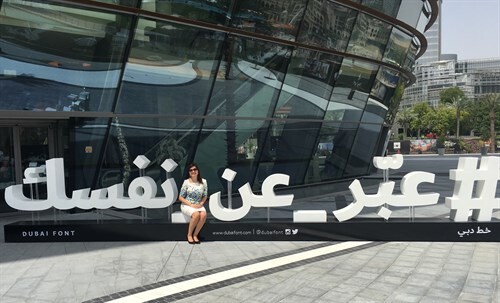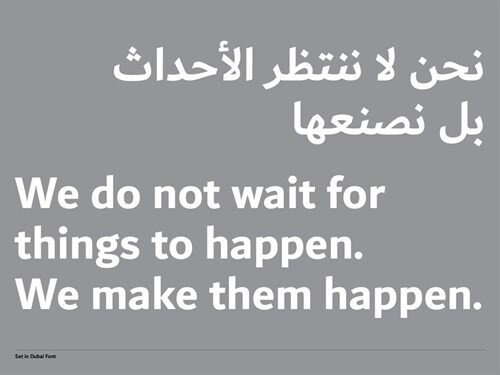
Dubai Font : une police de caractères d’avenir pour une ville et ses habitants
Le Conseil exécutif de Dubaï s’est associé à Microsoft et Monotype pour créer une famille de polices qui reflète la nature énergique et dynamique de Dubaï. Plus qu’une police de caractères gouvernementale, cette famille typographique - qui a été librement diffusée pour un usage public et est disponible dans Microsoft Office 365 - a été conçue pour être une voix harmonieuse à la fois dans les écritures latine et arabe.
Si plusieurs villes ont investi dans leurs propres polices de caractères sur mesure, ce qui distingue Dubai Font est son partenariat avec Microsoft et sa distribution gratuite pour l’usage public et gouvernemental. Alors que de nombreuses typographies urbaines ont pour cœur le tourisme ou une fonction utilitaire, Dubai Font va au-delà. Elle devient également une voix typographique pour la population qu’elle représente.
Pour Nadine Chahine, alors directrice typographe chez Monotype, le projet s’est également inscrit dans une perspective personnelle. Elle a vécu et enseigné à Dubaï, s’y rend régulièrement depuis 2005 et a été témoin de la croissance et du développement de la ville. La création d’une famille de polices sur mesure a été l’occasion d’exprimer une partie de la personnalité et de l’héritage de la ville, ainsi que de designer ses deux composantes - les caractères latins et arabes - main dans la main. Le plus souvent, les deux alphabets sont développés séparément, ce qui a donné à Dubai Font l’honneur d’être la première police de caractères intégrée dans Microsoft Office dont les alphabets latin et arabe ont été créés en même temps.
L’harmonie entre le latin et l’arabe était essentielle au design, et reflétait l’harmonie avec laquelle tant de nationalités différentes à Dubaï en sont venues à vivre ensemble.
Pour gérer ce processus, il a fallu des vérifications régulières avec les designers de l’équipe, échangeant des fichiers afin de s’assurer que les différents scénarios fonctionnaient ensemble. Donc travailler en harmonie pour développer le design global. De subtiles modifications du design ont été exigées afin de créer une compatibilité entre les deux écritures sans sacrifier l’authenticité de l’une ou l’autre. Par chance, certaines caractéristiques de l’arabe peuvent être joliment assorties à certains styles du design latin.
« En arabe, nous avons beaucoup de courbes peu profondes avec des changements de direction soudains. Ce type de caractéristiques était essentiel au design », explique Chahine. « Nous devions également garder une référence au mouvement du stylo, mais subtile, car c’est une police sans serif, donc peu calligraphique. »
La police de caractères devait faire référence à l’héritage arabe sans être trop traditionnelle, afin d’incarner la philosophie de Dubaï tournée vers l’avenir. Il était également essentiel qu’elle ne soit pas trop ornementale, afin qu’elle puisse fonctionner « comme une bonne bête de travail », comme le caractérise Chahine. « Il s’agit d’avoir un pied dans le passé et un pied dans le futur. On construit sur ce que l’on a, mais on regarde aussi vers l’avenir. »
« Il y a une certaine sérénité dans son design, tant en latin qu’en arabe. Il fallait cette tranquillité », ajoute-t-elle.
Son ton modéré lui confère d’ailleurs une grande adaptabilité. Elle est capable de fonctionner dans le large éventail d’utilisations qu’elle aura potentiellement à terme - tant entre les mains du Conseil exécutif que du public. Chahine espère en particulier que la police de caractères trouvera un rôle dans le monde de l’éducation, sa nature calme offrant un passage potentiellement persuasif et accueillant vers l’apprentissage.
Bien au-delà, Chahine voit la Dubai Font comme une réalisation vers un objectif culturel plus élevé, tourné à destination du nombre décroissant de personnes qui lisent et utilisent l’arabe.
« Cela montre que l’arabe peut être contemporain », explique-t-elle. « Les gens le considèrent parfois comme démodé et dépassé, et si nous avons des polices de caractères qui montrent que la langue peut être représentée de manière moderne, alors cela pourrait être une façon d’inviter les gens à lire à nouveau en arabe. »
« C’est un excellent exemple de ce qu’une ville arabe contemporaine peut faire en matière de communication autour de l’arabe », ajoute-t-elle. « Cela invite à voir ce que l’arabe moderne peut être pour les gens, et montre l’étendue des champs d’actions pour la typographie et la culture. »
Pour promouvoir le lancement de Dubai Font, la municipalité a installé des lettres monumentales, tirées de la police de caractères, dans toute la ville - encourageant les gens à s’arrêter, prendre des photos et entrer en interaction avec la typographie d’une manière complètement différente. La population de Dubaï a adhéré à la police de caractères avec enthousiasme, les marques et les entreprises s’empressant d’être les premières à adopter la police officielle de la ville - lui prêtant aussi un air de patriotisme.
“ Voir la police adoptée par le public, et pas seulement par les graphistes, c'est ce que je préfère dans tout ça. ”
Nadine Chahine.
La police de caractères Dubai Font reflète une évolution réelle dans la perception de la typographie et dans l’appréciation des possibilités qu’elle offre, tant du point de vue culturel que de celui de la communication.
« C’est formidable de voir le gouvernement soutenir la typographie et le rôle de l’innovation typographique », ajoute Chahine. « Voir la typographie comme un élément de communication et d’expression, et la voir adoptée par le public, et pas seulement par les graphistes, c’est ce que préfère dans tout ça. »
« C’est super de voir la typographie devenir le sujet de conversation principal de personnes ordinaires. »